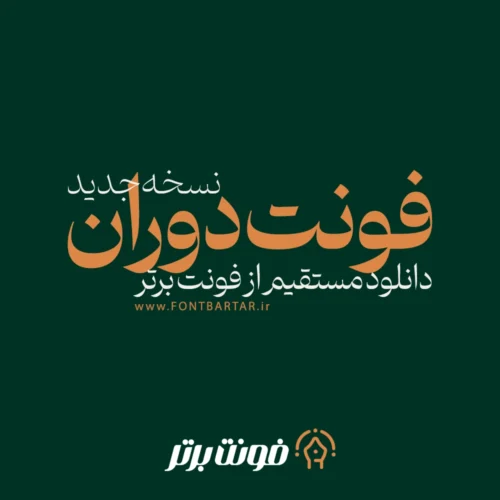
دانلود فونت دوران
فونت فارسی دوران یکی از جدیدترین و جذابترین فونتهای مدرن است که با طراحی منحصربهفرد خود توانسته توجه طراحان گرافیک، تولیدکنندگان محتوا و برندهای خلاق را جلب کند. فونت جدید با الهام از سادگی و زیبایی تایپوگرافی کلاسیک طراحی شده و در عین حال روحی مدرن و امروزی به نوشتههای شما میبخشد.
اگر به دنبال یک فونت حرفهای برای پروژههای تبلیغاتی، طراحی پوستر، لوگوتایپ یا استوریهای شبکههای اجتماعی هستید، فونت دوران یک انتخاب عالی است.
ویژگیهای فونت دوران
- طراحی مدرن، روان و چشمنواز
- مناسب برای لوگو، پوستر، جلد کتاب، تایپوگرافی و تبلیغات دیجیتال
- خوانایی بالا در متنهای طولانی و کوتاه
چرا فونت دوران انتخاب مناسبی است؟
خرید فونت دوران با ترکیب نوستالژی و مدرنیته، حس اعتماد، اصالت و زیبایی را به نوشتهها منتقل میکند. این فونت برای برندهایی که به دنبال خاص بودن و ماندگاری در ذهن مخاطب هستند، بهترین گزینه است. استفاده از فونت دوران میتواند به پروژههای شما هویت و شخصیت منحصربهفردی ببخشد.
کاربردهای فونت دوران
- طراحی لوگو و هویت بصری برند
- فونت جدید برای اینشات
- ساخت پوسترهای تبلیغاتی و هنری
- تایپوگرافی خلاقانه برای شبکههای اجتماعی
- طراحی جلد کتاب و محصولات چاپی
- استفاده در مقالات، بروشورها و کاتالوگها
- مناسب برای وبسایتها و رابط کاربری مدرن